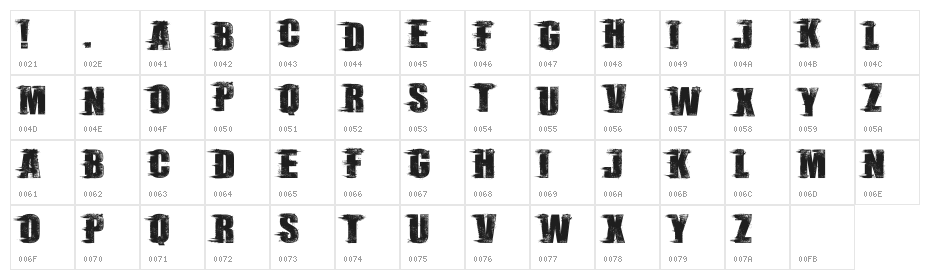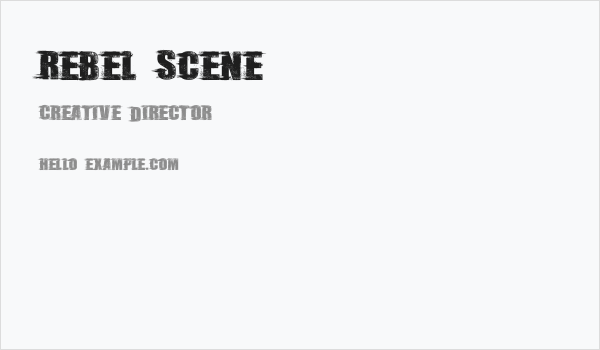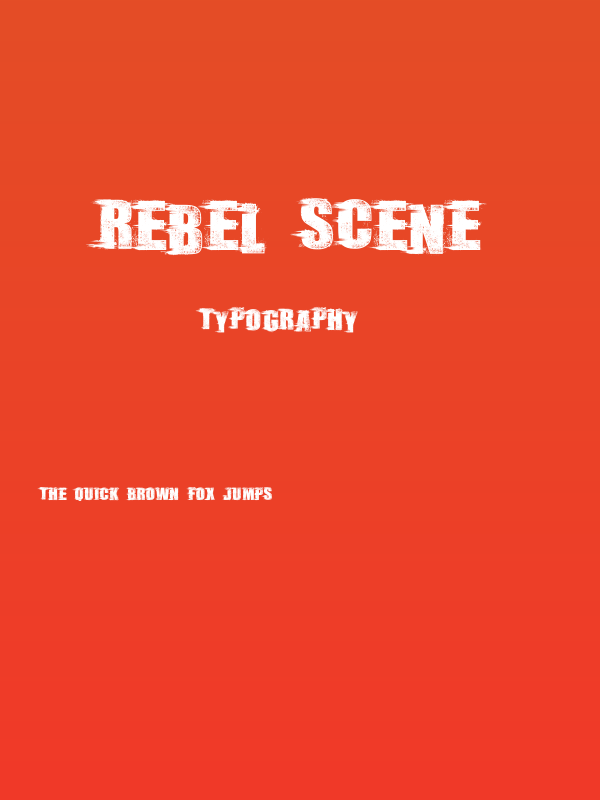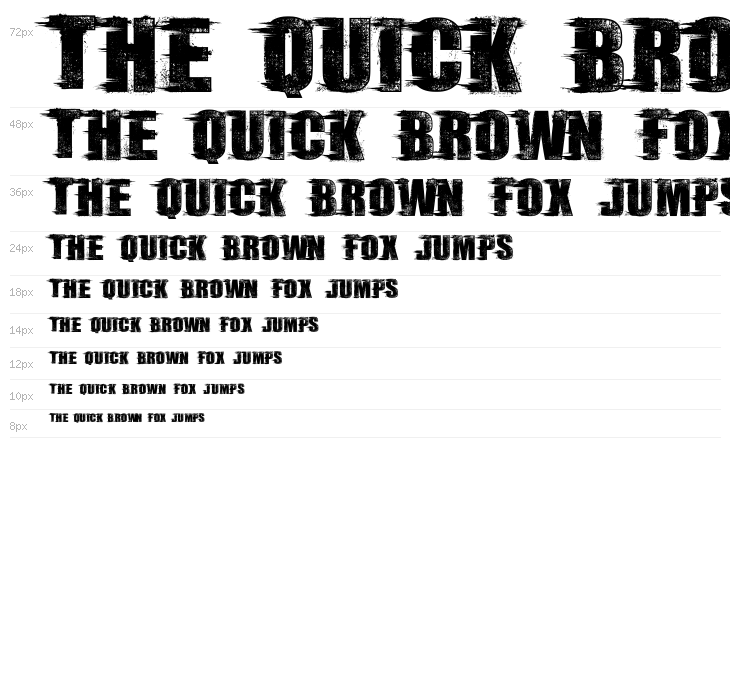
Rebel Scene Font
| Stile generale | Grunge, Edgy, Rebellious |
| Progetti proposti | Ideal for music album covers, posters, streetwear branding, and any project needing a bold, edgy aesthetic. |